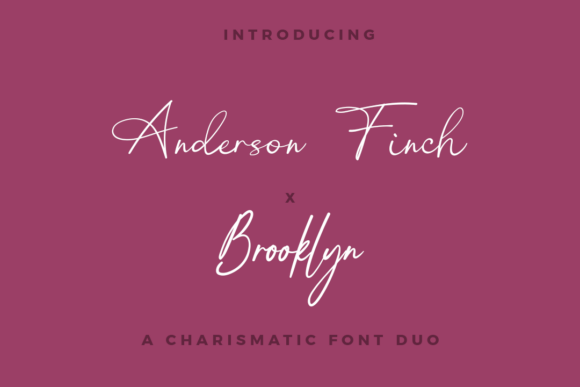
Anderson Finch X Brooklyn Duo
Поиск подходящих элементов дизайна может быть сложным, но Anderson Finch X Brooklyn Duo предлагает исключительную коллекцию, которая мгновенно улучшит вашу работу.
Создаете ли вы продукты POD (печать по требованию), свадебные приглашения или графику для социальных сетей, Anderson Finch X Brooklyn Duo станет идеальным выбором.